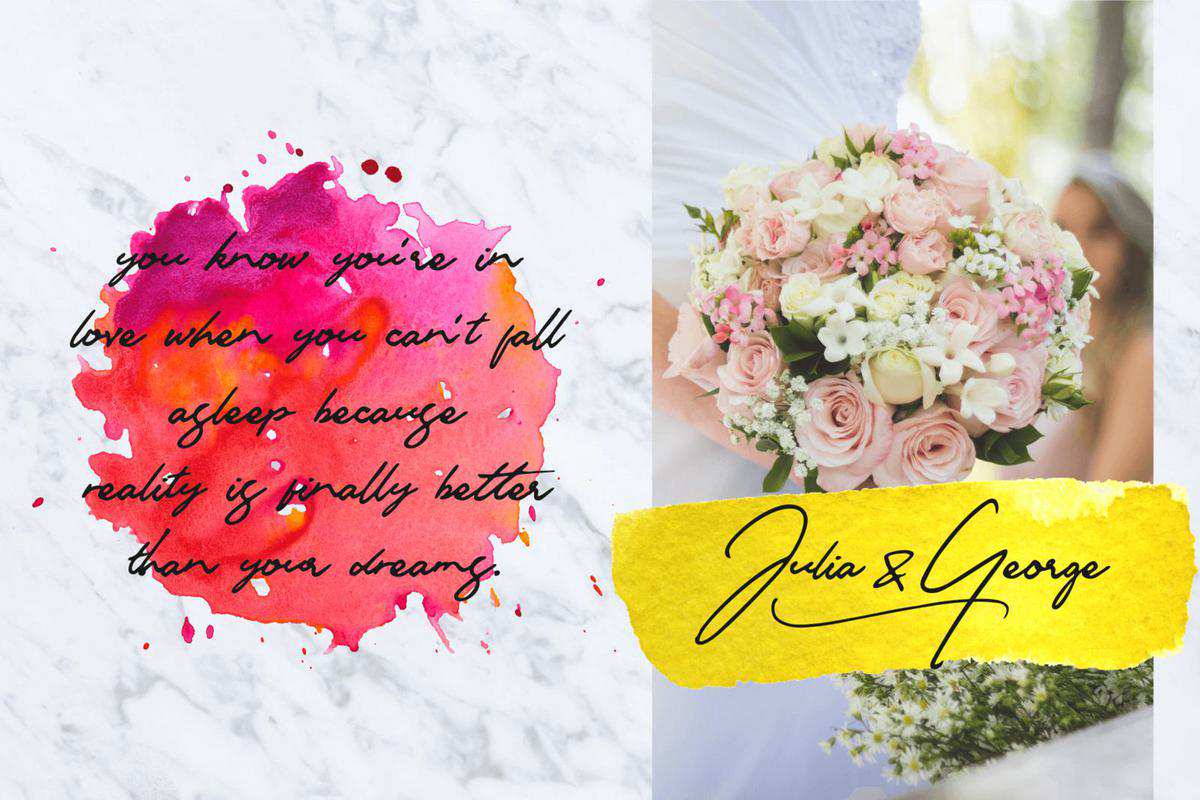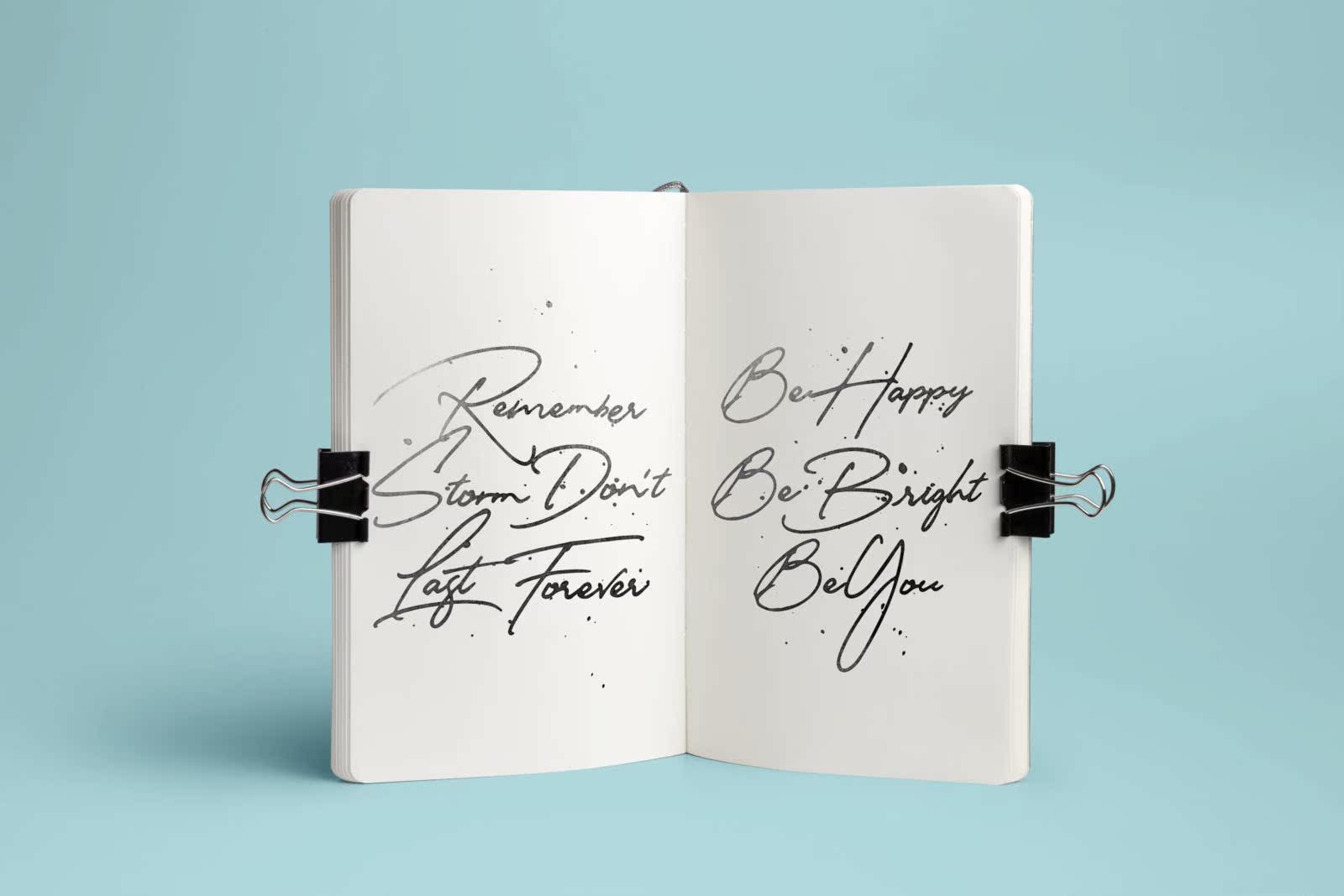
Matsury是一款精美的签名手稿。100%手工制作,让您感受到完美的组织形状。这款手稿将完美满足您的任何设计项目需求。例如,徽标、标题、报价、婚礼卡、,还有更多。Matsury将具有不完整的字符。因此,您可以混合和组合。Matsury是一种合法的签名手稿。100%手工制作,让您感觉组织形状合适。此字体将完美满足您的任何设计项目需要。例如,徽标、标题、引用、婚礼卡,而且,更多的。Matsuryal也可以使用Buncho替代字符停止与。Soy混合和组合。